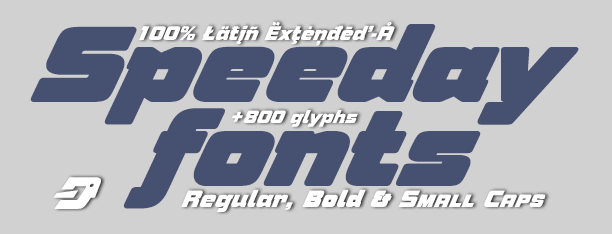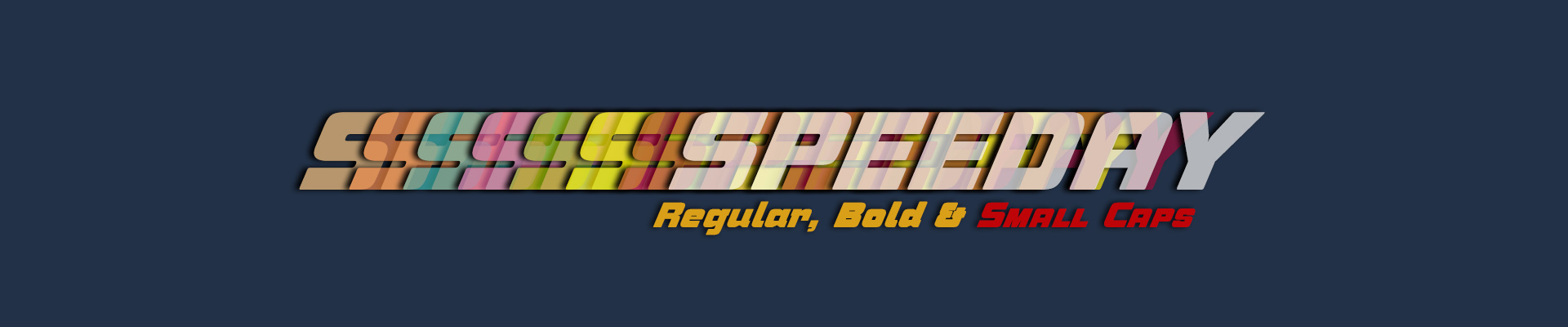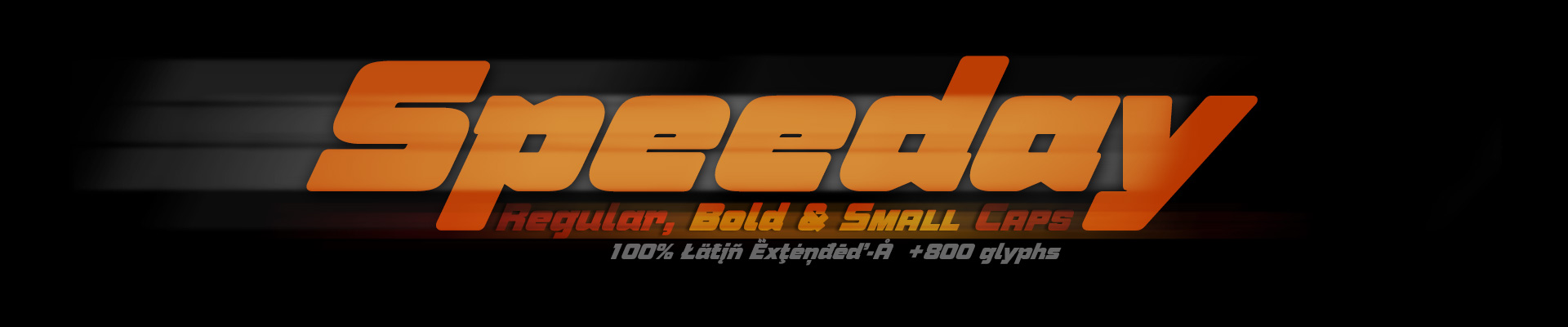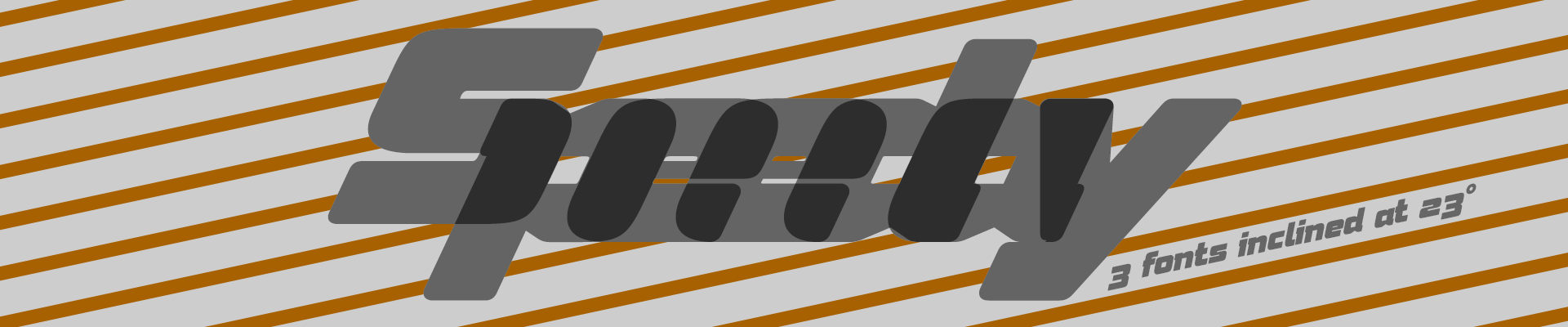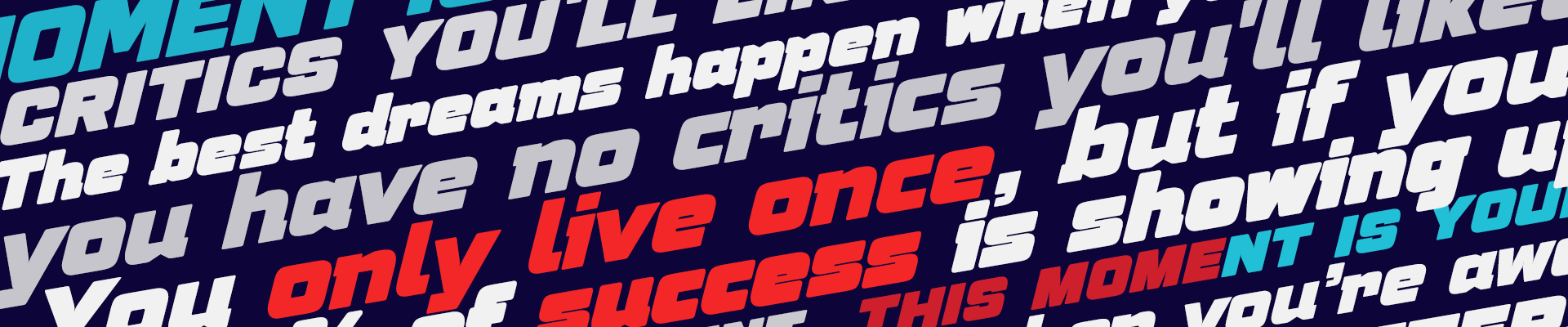
Estilo: Sans Serif, Small Caps, Display, Inclined
Proporción: Regular, Bold, Italic, Versalita
Glyphs: 845
Alternates: 163
Latin-Extended: Latín Básico, Europa Occidental, Central & Oriental.
Autor: deFharo
Funciones OpenType: Additional languages, All Alternates, Alternate Annotation Forms, Bitcoin, Capital Spacing, Contextual Alternates, Denominators, Discretionary Ligatures, Extended Fractions, Historical Forms, Inferiors, Kerning, Localized Forms, Numerators, Oldstyle Figures, Ordinals, Petite Caps, Scientific Inferiors, Slashed Zero, Small Capitals, Small Capitals From Capitals, Standard Ligatures, Stylistic Set, Subscript, Superior letters, Superiors, Superscript, Titling alternates.
• Latin Extended-A & Open Type Features •
Tipografía gruesa de aspecto contemporáneo que proporciona gran dinamismo a los textos escritos con ella, su uso en diseño gráfico, editorial y publicidad garantiza originalidad, diferencia y máxima legibilidad, el kerning ha sido configurado cuidadosamente en todas las versiones.
Unas fuentes muy versátiles para carteles publicitarios, vídeo juegos, títulos de cine, logotipos, publicaciones, etc. Incluyen el símbolo del Bitcoin y otras Cripto Monedas.
La fuente «Speeday Regular dispone en su versión comercial de un juego de 845 glifos (Latin Extended-A), la versión en versalita 822 glifos y 790 glifos para la versión Bold, todas ellas con soporte para cualquier idioma europeo o centro europeo.
Speeday también incluye funciones OpenType (Compatibles con InDesign, QuarkXpress, Photoshop e Illustrator.